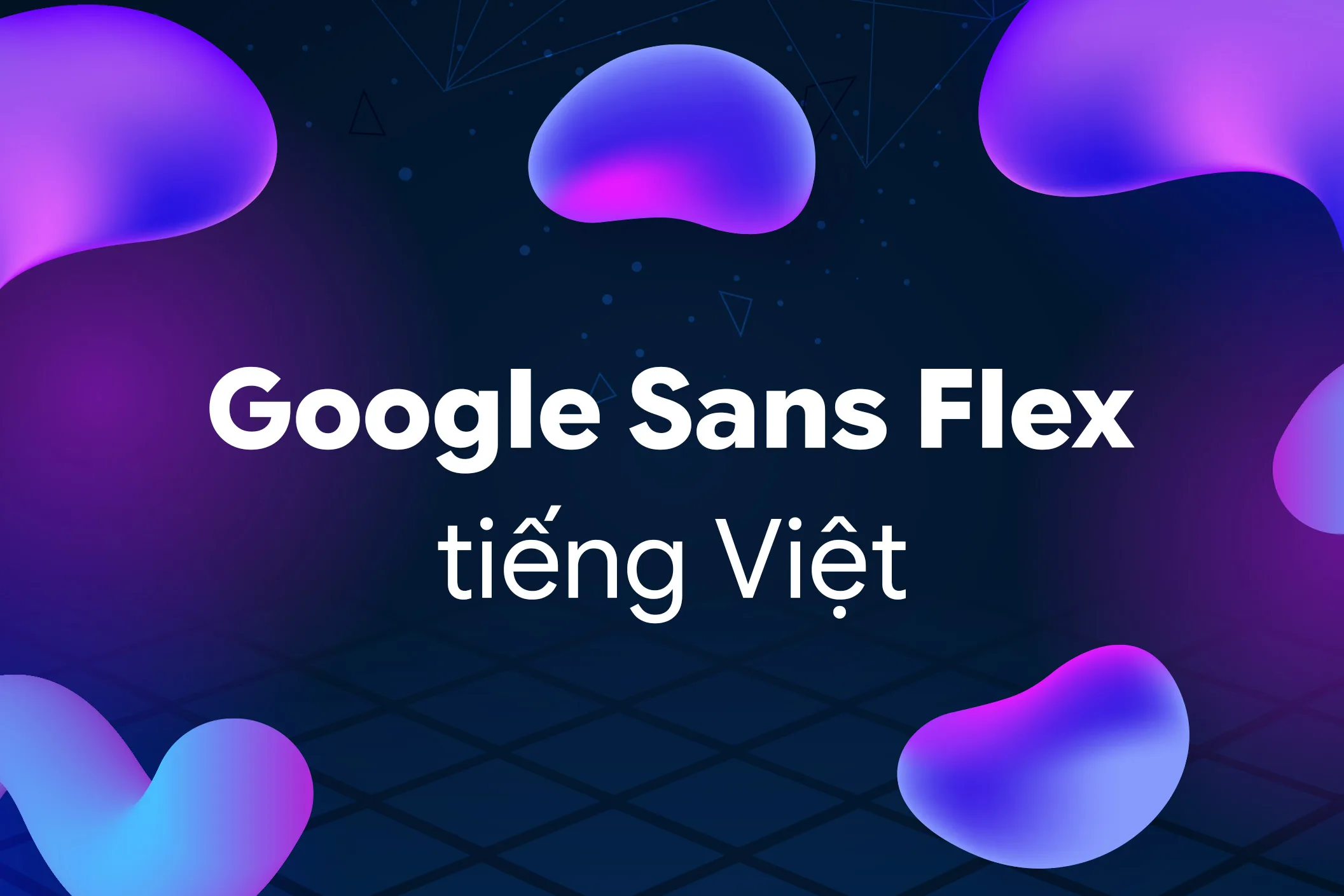
Google Sans Flex tiếng Việt
Nâng tầm giao diện với Google Sans Flex – Variable font thế hệ mới từ Google. Tùy chỉnh độ đậm, nhạt, nghiêng linh hoạt chỉ trong một file duy nhất. Hỗ trợ Tiếng Việt hiển thị sắc nét, hoàn hảo trên mọi thiết bị.